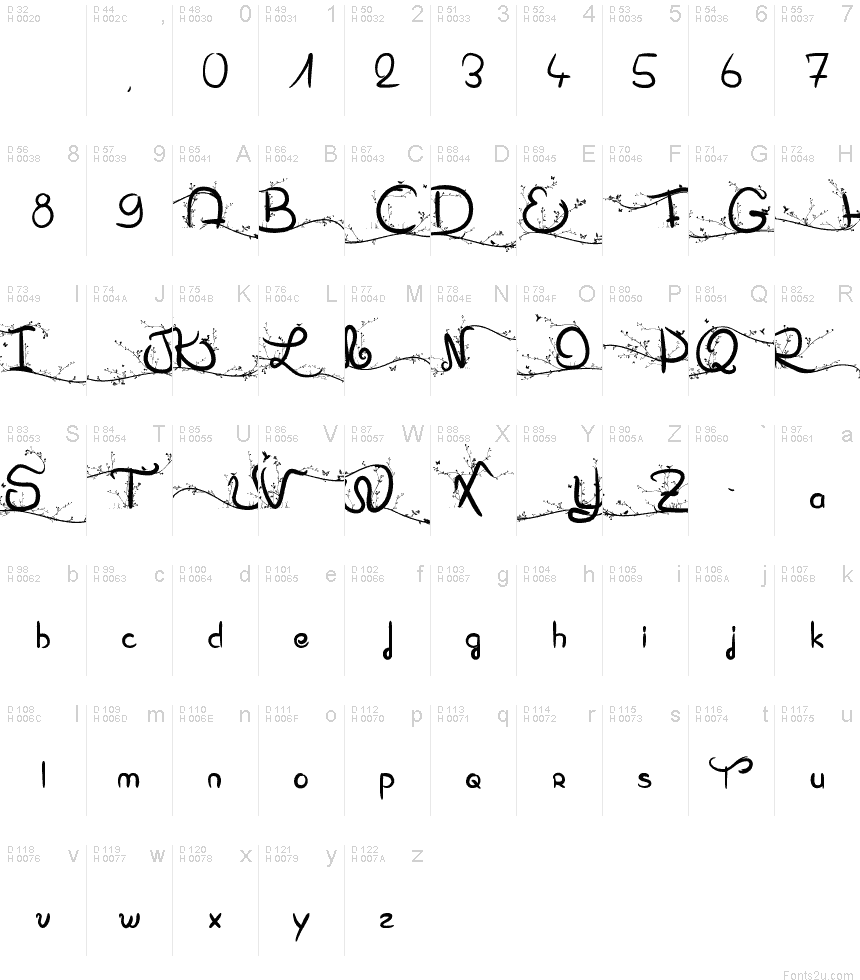
Eglantine to bezpłatny, ozdobny krój displayowy, którego litery przeplatają się z winoroślami, drobnymi listkami i trzepoczącymi ptakami. Zamaszyste krzywe sprawiają wrażenie rysowanych ręcznie i nieco dzikich, jakby każde słowo wyrosło prosto z baśniowego lasu. Wszędzie, gdzie się pojawi, wprowadza natychmiastowe poczucie magii i organicznego uroku. Dzięki Eglantine nadasz bujny, fantazyjny charakter okładkom baśni, plakatom fantasy, zaproszeniom ślubnym, logotypom inspirowanym naturą, opakowaniom butikowym, oznakowaniom wydarzeń czy tytułom w mediach społecznościowych. Ten darmowy font najlepiej prezentuje się w dużym rozmiarze jako nagłówek; w tekście głównym połącz go z prostym, neutralnym krojem bezszeryfowym, aby zachować czytelność i elegancję projektu.
Eglantine